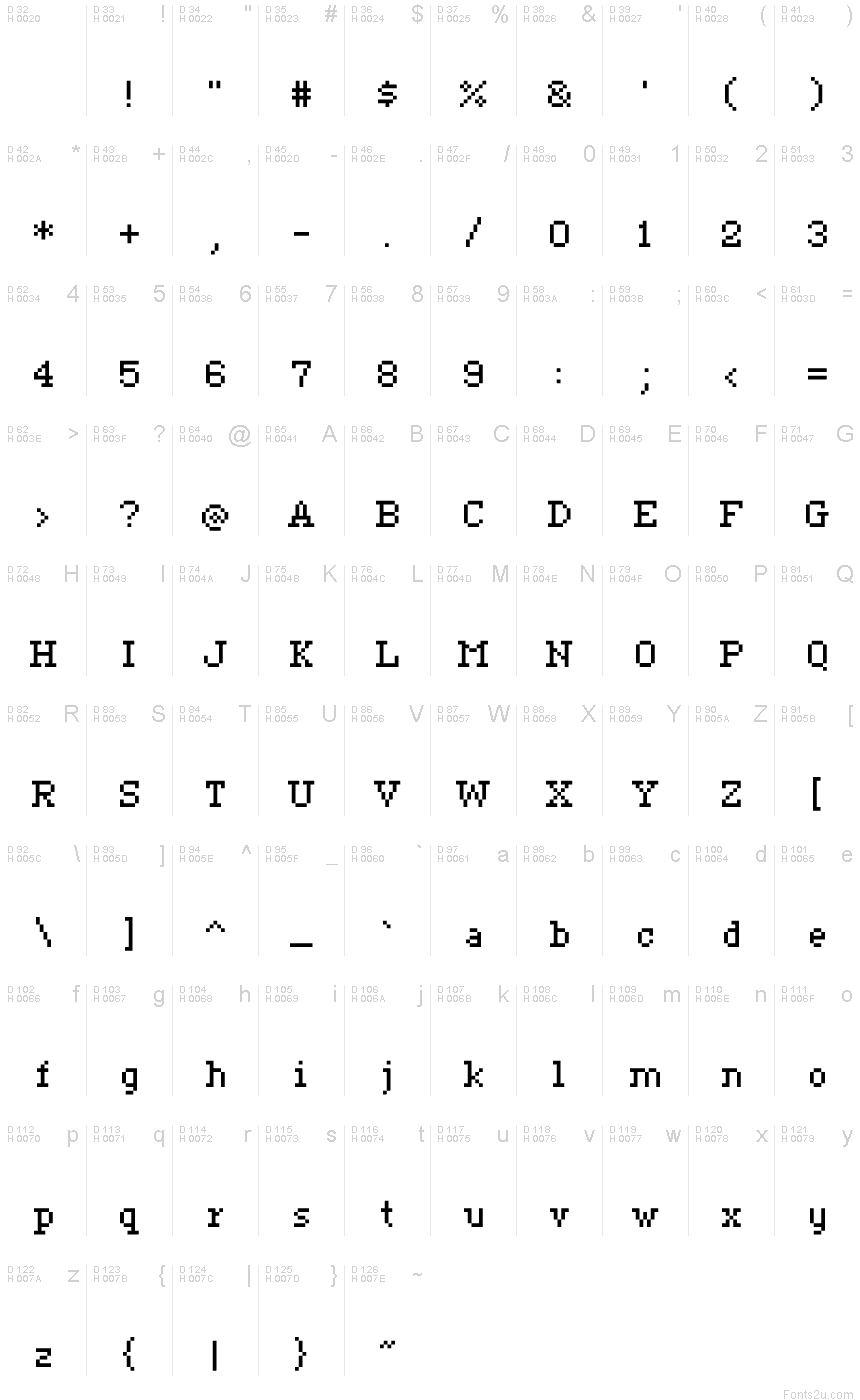
Podgląd czcionki ceriph 07_56
Ceriph 07 56 autorstwa Craiga Kroegera to darmowy krój typu pixel serif, który przywodzi na myśl surowy klimat wczesnych ekranów komputerowych. Litery łączą w sobie masywne, kwadratowe kształty z solidnymi szeryfami, dzięki czemu font balansuje na pograniczu użytkowej grafiki bitmapowej i ascetycznego stylu maszyny do pisania.
Doskonale sprawdzi się w interfejsach gier retro, nagłówkach zinów, odznakach internetowych, plakatach inspirowanych oprogramowaniem oraz krótkich hasłach, gdzie darmowy font z widocznymi pikselami pozwala szybko nadać odpowiedni charakter. Wykorzystaj go w tytułach, etykietach menu lub kompaktowym brandingu, jeśli szukasz wyrazistego, blokowego rytmu bez wpadania w typowo techno-estetykę.